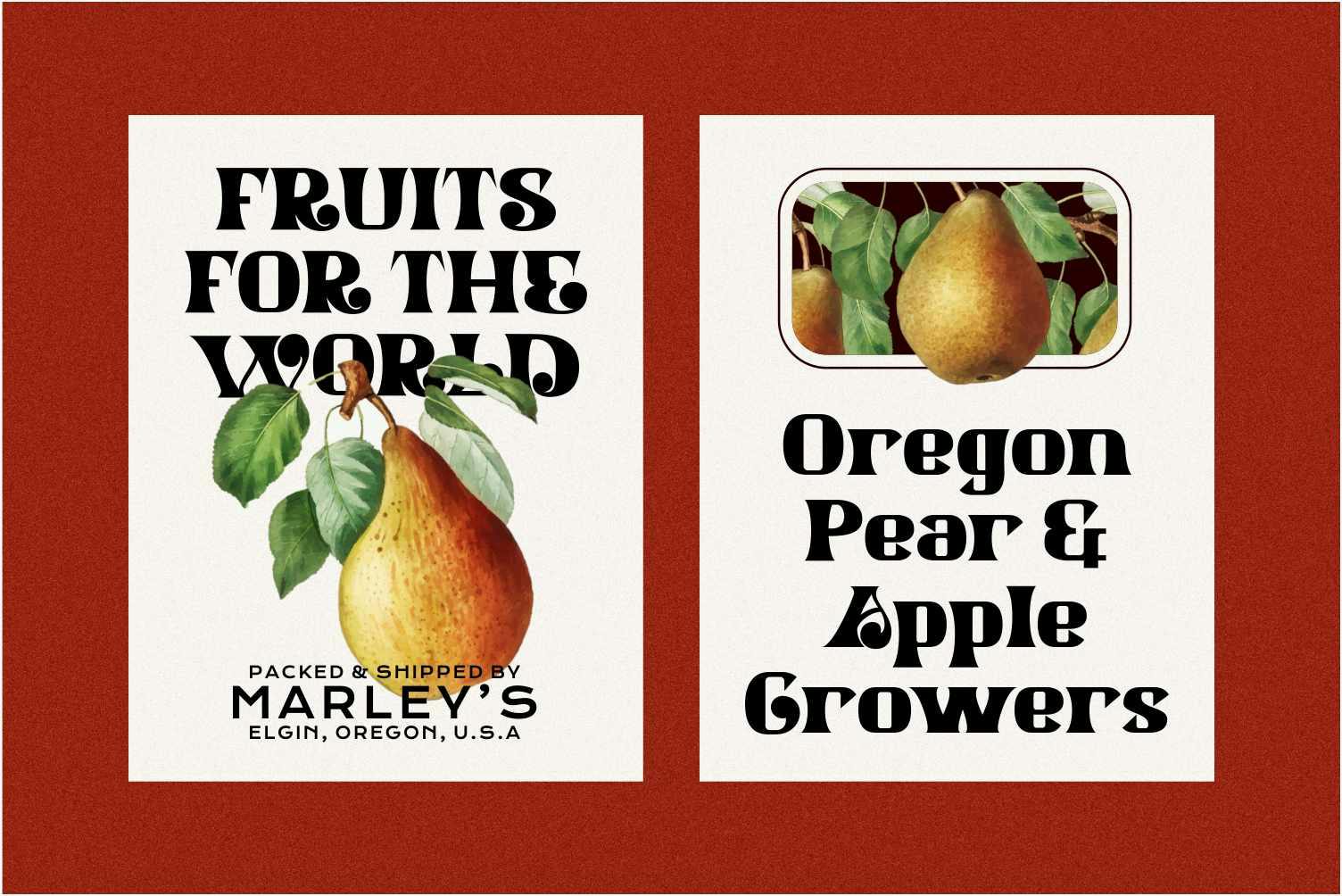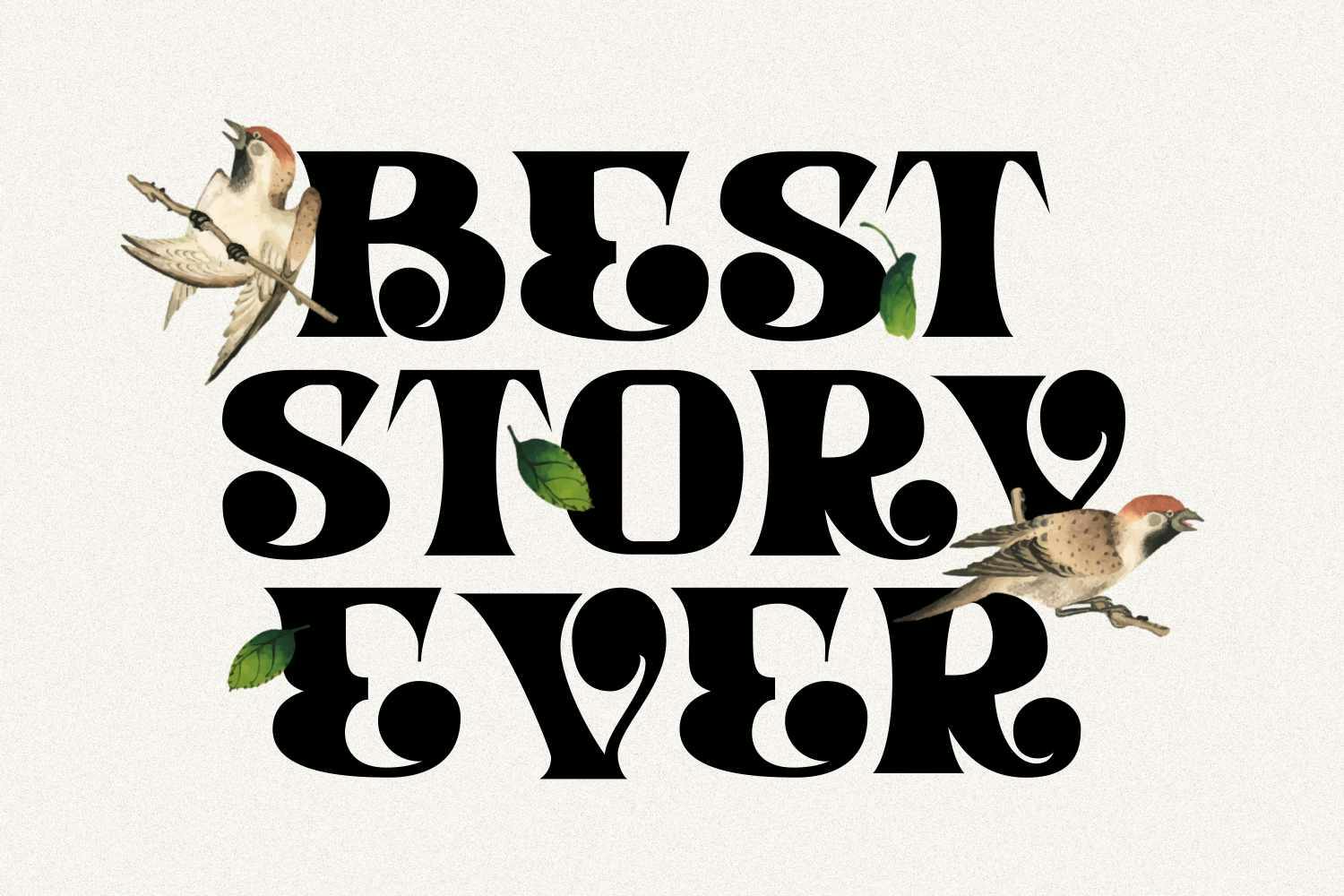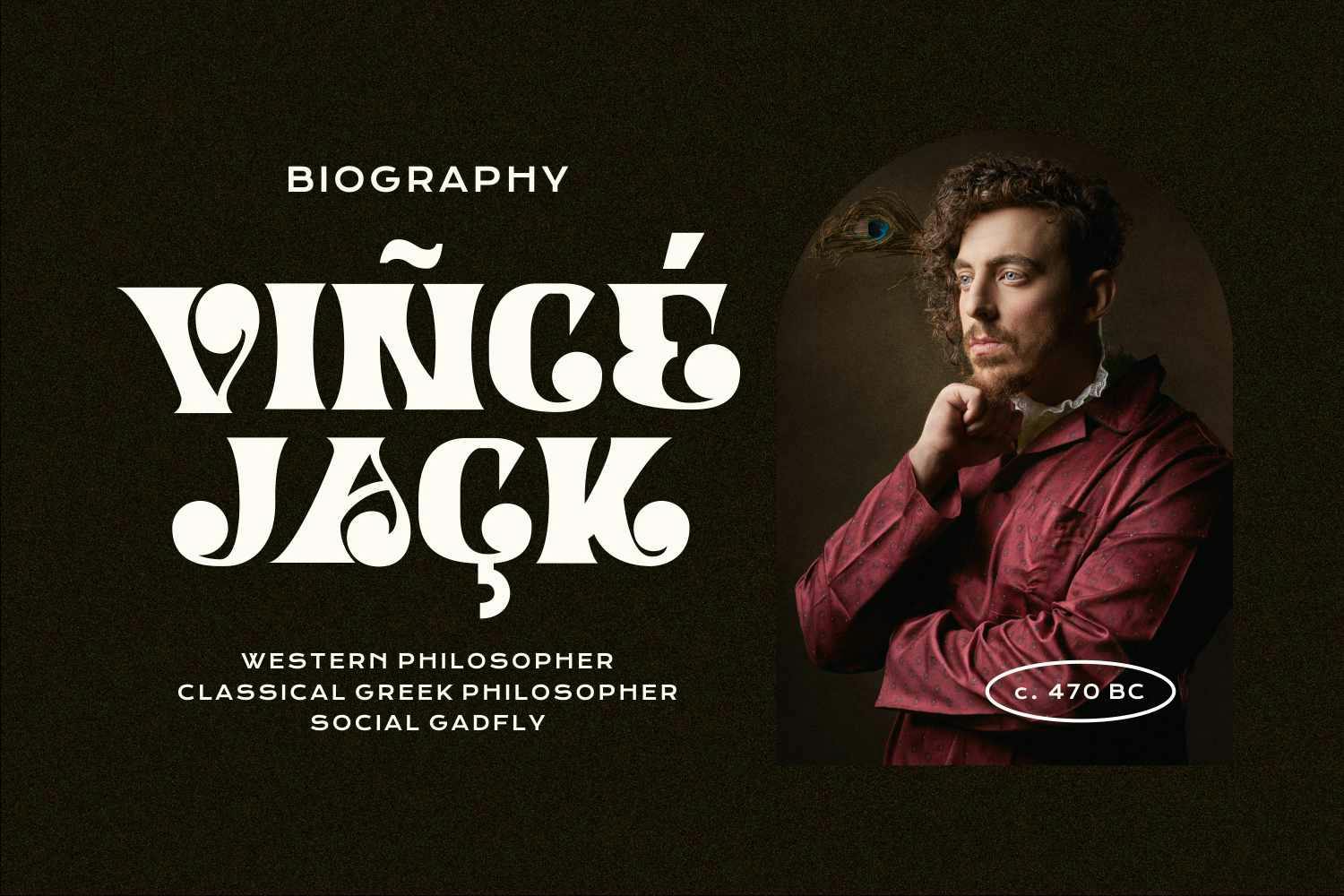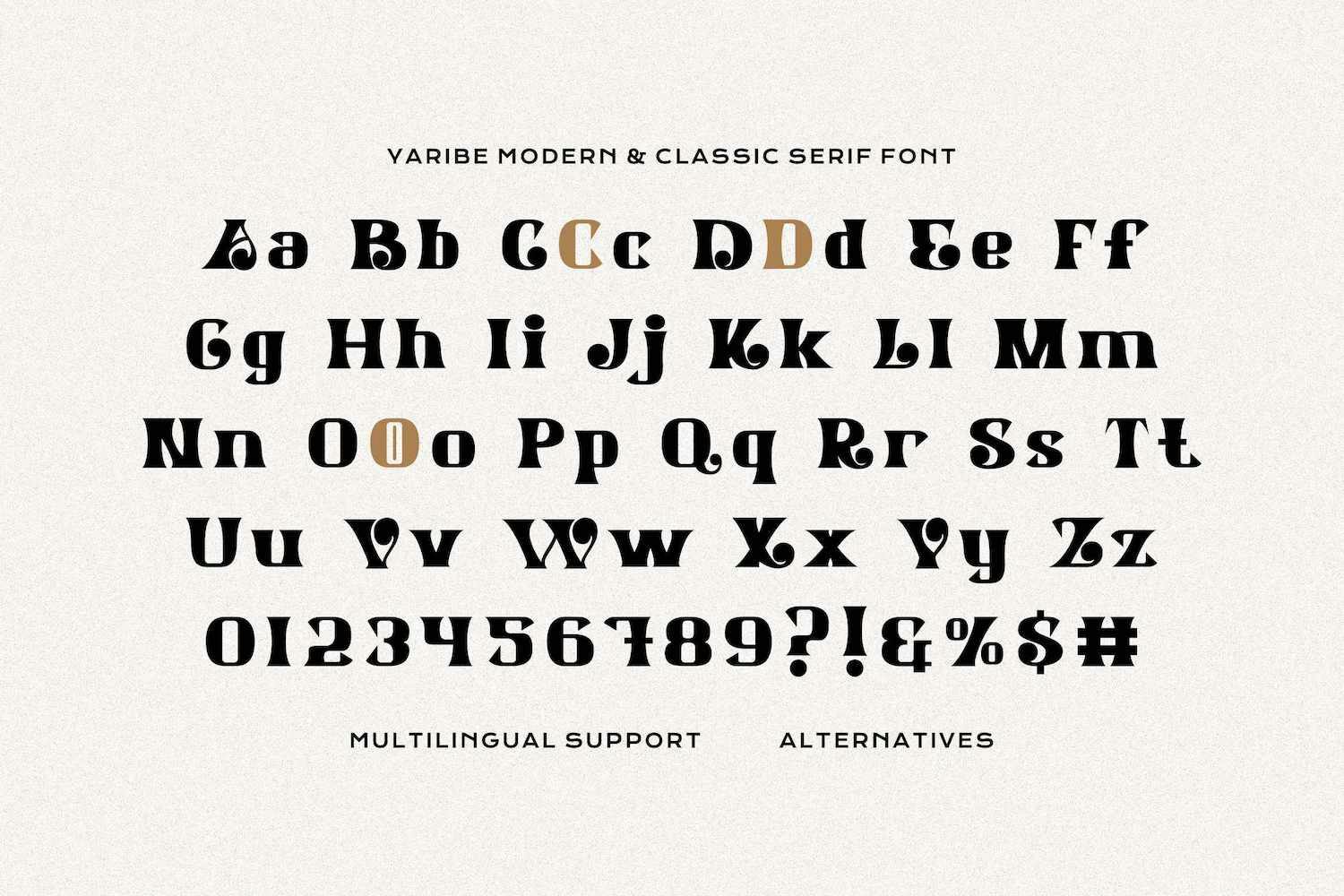
محصول فونت Yaribe برای بسیاری از پروژههای شما مانند طراحی لوگو و برندینگ، عکاسی، دعوتنامهها، واترمارکها، تبلیغات، طراحی محصولات، لوازمالتحریر، طراحیهای عروسی، برچسبها، بستهبندی محصولات، رویدادهای خاص و بیشتر مناسب است.